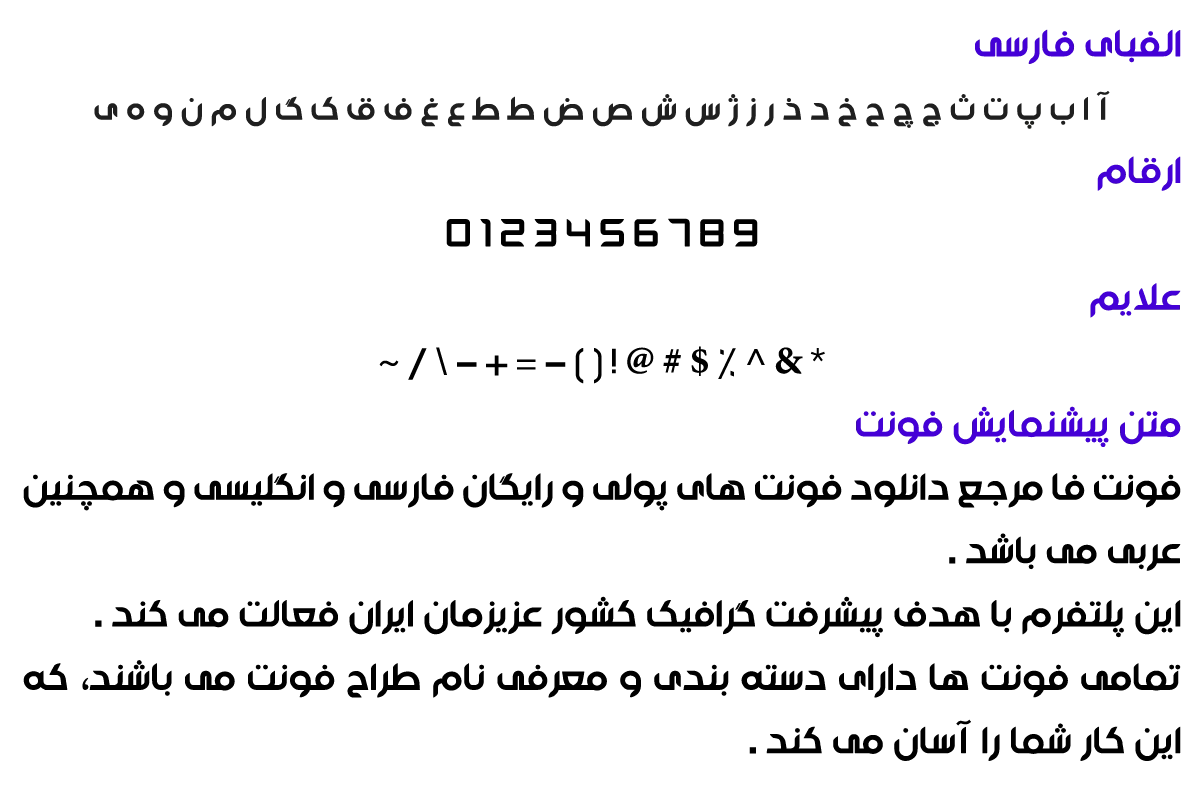
فونت فارسی تبریز – Tabriz
توضیحات و معرفی فونت تبریز
فونت فارسی تبریز ( Tabriz ) از مجموعه فونت های آزاد می باشد، همچنین نوع فونت هندسی می باشد.
تایپ فیس معرفی شده نسخه پارسی شده فونت منادی است که حروف گ چ پ ژ به آن اضافه شده است.
همچنین این فونت در یک وزن معمولی است.